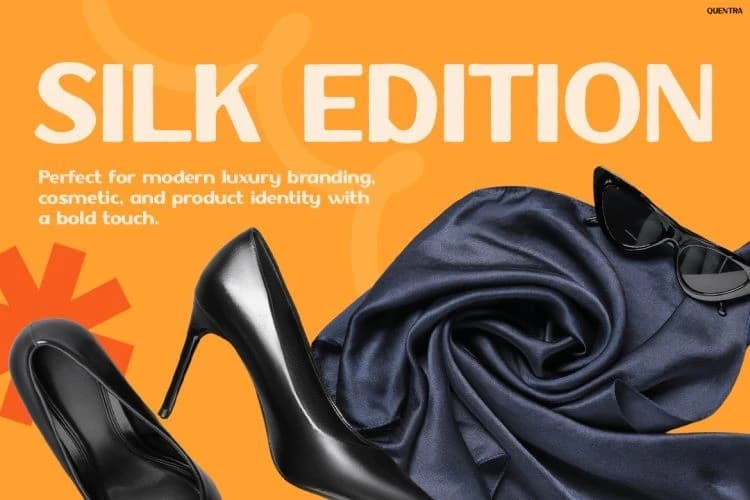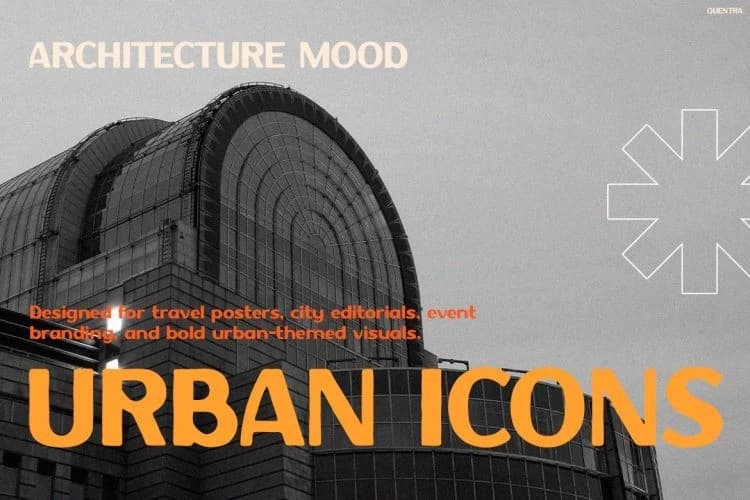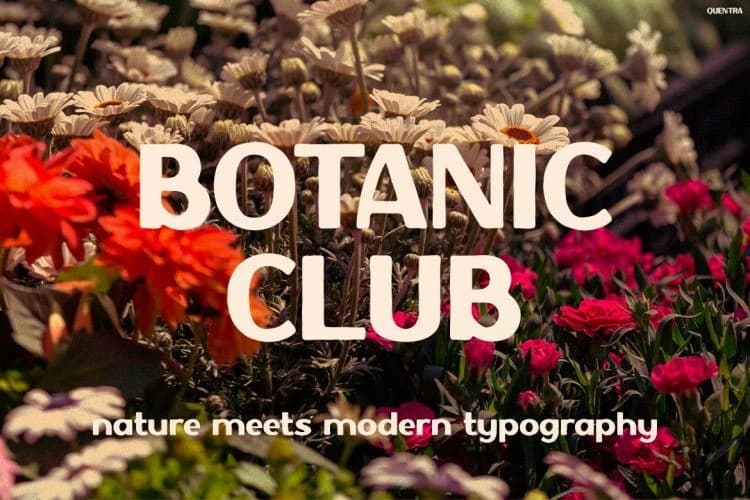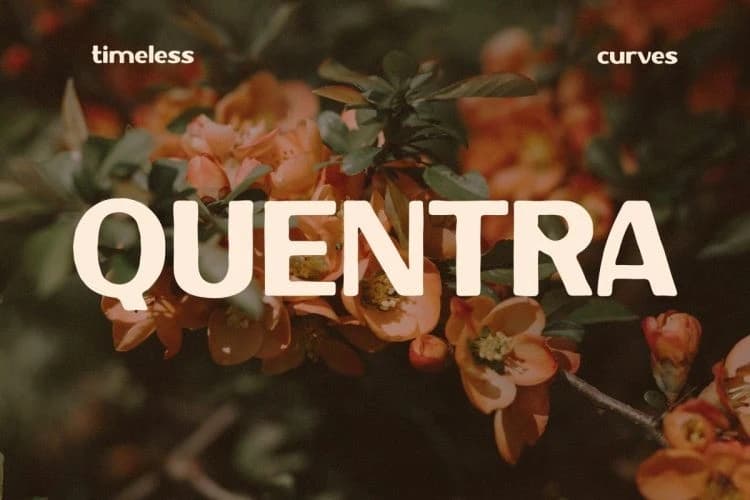
QUENTRA Font, zamansız retro havasını temiz modern bir yapı ile harmanlayan şık bir yazı tipidir. İlk bakışta, akıcı eğriler ve dengeli oranlar zarif fakat cesur bir görsel etki yaratır.
QUENTRA Font, zamansız retro havasını temiz modern bir yapı ile harmanlayan şık bir yazı tipidir. İlk bakışta, yumuşak eğrileri ve dengeli oranları zarif ama cesur bir görsel etki yaratır.